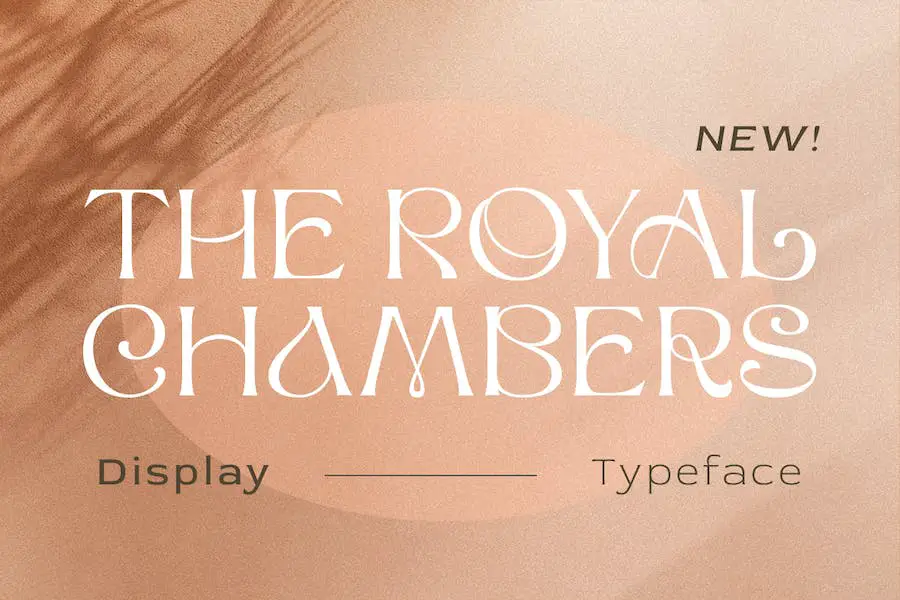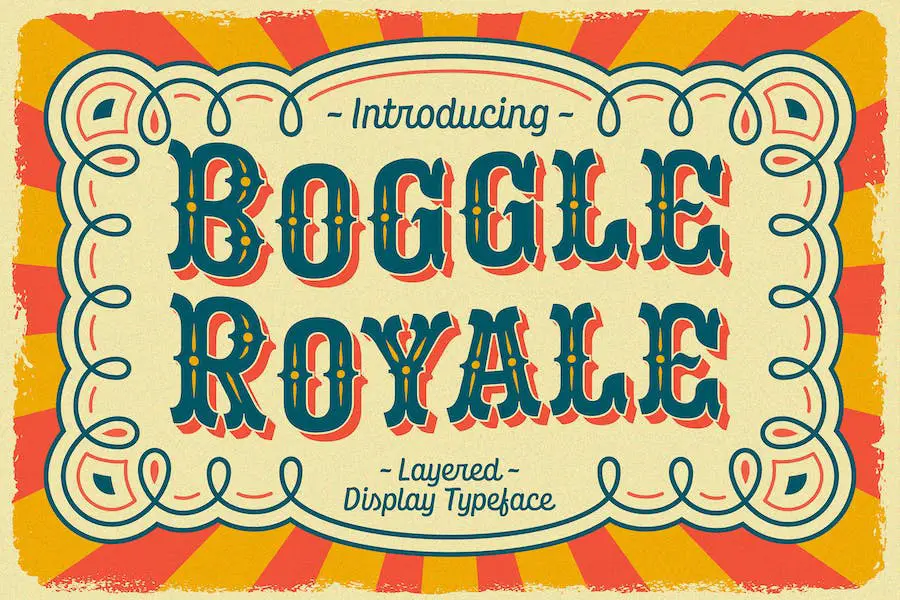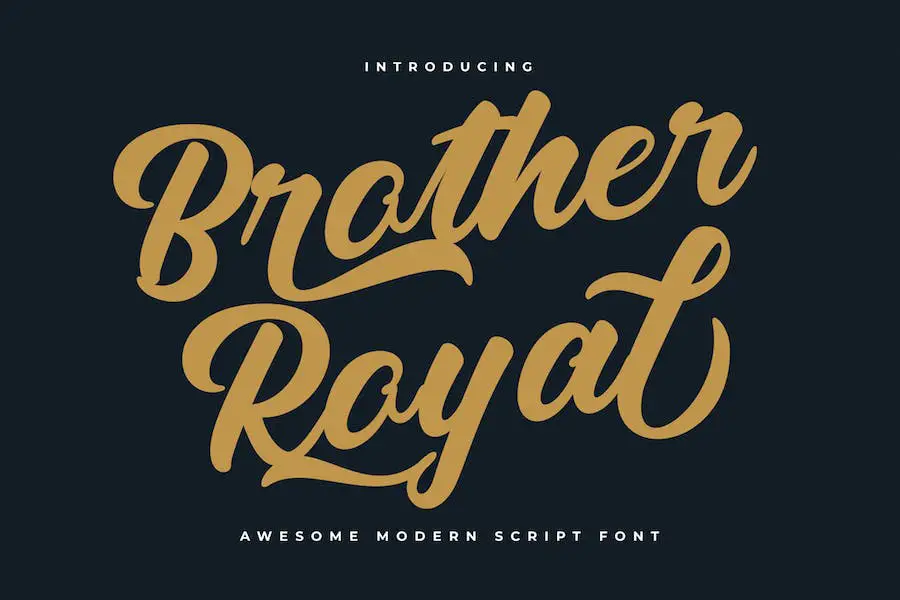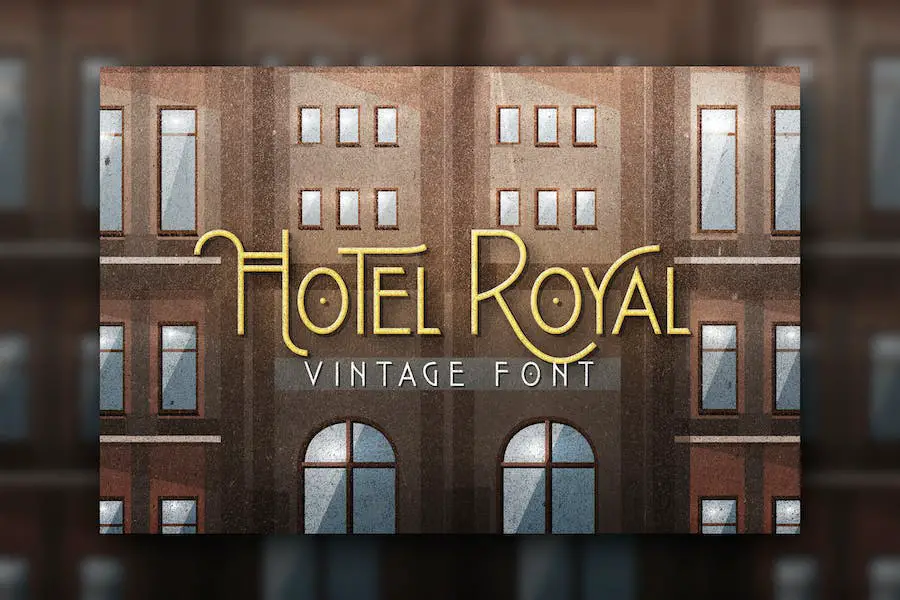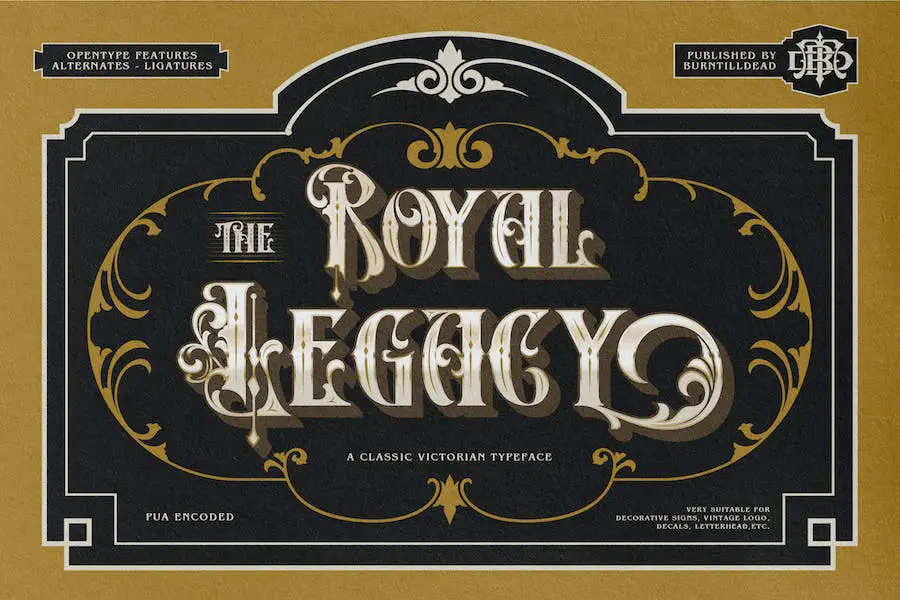
2023'ün En İyi 20 Kraliyet Yazı Tipi (Ücretsiz ve Premium)
Yayınlanan: 2023-09-10Projelerinizi bir sonraki seviyeye taşımak için mükemmel yazı tipini arayan bir grafik tasarımcı mısınız? Başka yerde arama! Bu blog yazısında sizi hem ücretsiz hem de premium seçeneklerle 2023'ün en iyi 20 royal yazı tipiyle tanıştıracağız. Ama merak ediyor olabilirsiniz, neden kraliyet yazı tiplerine ihtiyacım var?
Peki, konuya dalalım. Kraliyet yazı tipleri, projenizin tasarımını yükseltmenin ve ona zarafet ve gelişmişlik dokunuşu katmanın harika bir yoludur.
İster bir logo, web sitesi veya baskı tasarımı üzerinde çalışıyor olun, doğru yazı tipi seçimi büyük fark yaratabilir. Bu yazı tipleri kraliyet ailelerinin muhteşem estetiğinden ilham almıştır ve lüks ve gösterişli bir görünüm yaratmak için mükemmeldir.
Şimdi ayrıntılara geçelim. Bu yazımızda tasarımlarınızda kullanabileceğiniz 20 muhteşem royal yazı tipini sizlere sunacağız. İhtiyaçlarınıza ve bütçenize uygun mükemmel yazı tipini bulabilmeniz için size hem ücretsiz hem de premium seçenekler sunacağız.
Her yazı tipine kısa bir açıklama ve nasıl etkili bir şekilde kullanılabileceğine dair örnekler eşlik edecektir.
Öyleyse bir fincan kahve alın ve tasarımlarınızı sanat eserlerine dönüştürecek bu muhteşem kraliyet yazı tiplerinden ilham almaya hazırlanın. Gelin krallara ve kraliçelere uygun tipografi dünyasına dalalım ve keşfedelim!
En İyi Premium Royal Fontlar
Zarafet ve ince zevkin mükemmel bir uyum içinde buluştuğu Royal Fonts dünyasına hoş geldiniz. Bu bölümde tasarım projelerinize asil bir dokunuş katacak en iyi premium kraliyet yazı tiplerini sergiliyoruz.
Hedef kitlenizi büyüleyecek ve tasarımlarınızı yeni boyutlara taşıyacak bu muhteşem yazı tiplerini keşfedin ve keşfedin. Bu çarpıcı yazı tiplerini keşfetmek ve görsel hikaye anlatımının gerçek gücünün kilidini açmak için bir dakikanızı ayırın.
Kraliyet Dokunuşu
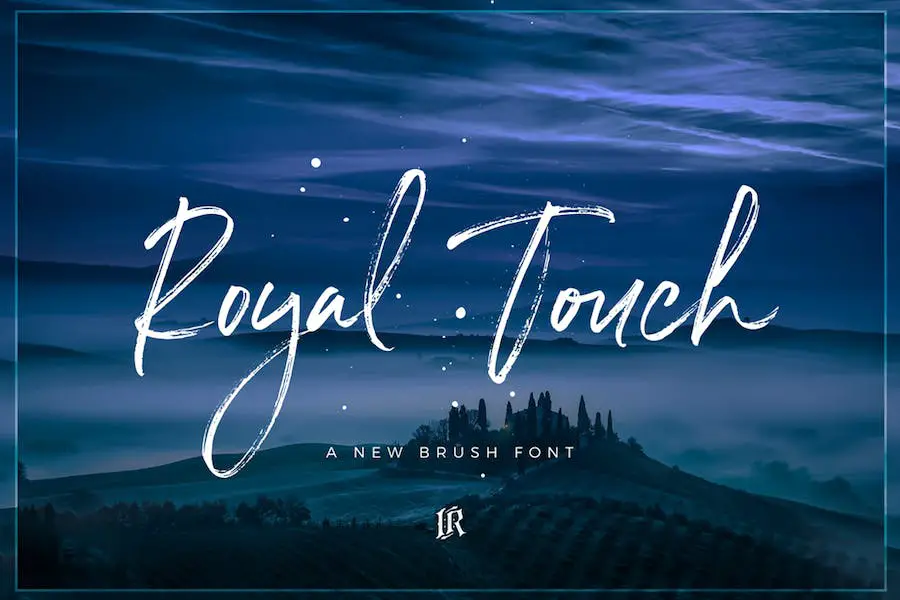
Royal Touch, her türlü tasarım projesine zarafet katacak, elle fırçalanmış çarpıcı bir yazı tipidir.
İster kraliyet temalı bir logo tasarlıyor olun, ister web siteniz için içerik oluşturuyor olun, ister bir dövme tasarımı üzerinde çalışıyor olun, Royal Touch mükemmel bir seçimdir. Zarif ve sofistike tarzı, projenizin kalabalığın arasından sıyrılmasına ve kalıcı bir izlenim bırakmasına yardımcı olacaktır.
Bu yazı tipini diğerlerinden ayıran şey çok yönlülüğü ve kullanım kolaylığıdır. Adobe Illustrator ve Google Fonts gibi çeşitli tasarım yazılımlarına kolayca entegre edilebildiği için her seviyeden tasarımcının erişimine açıktır.
Le Royale
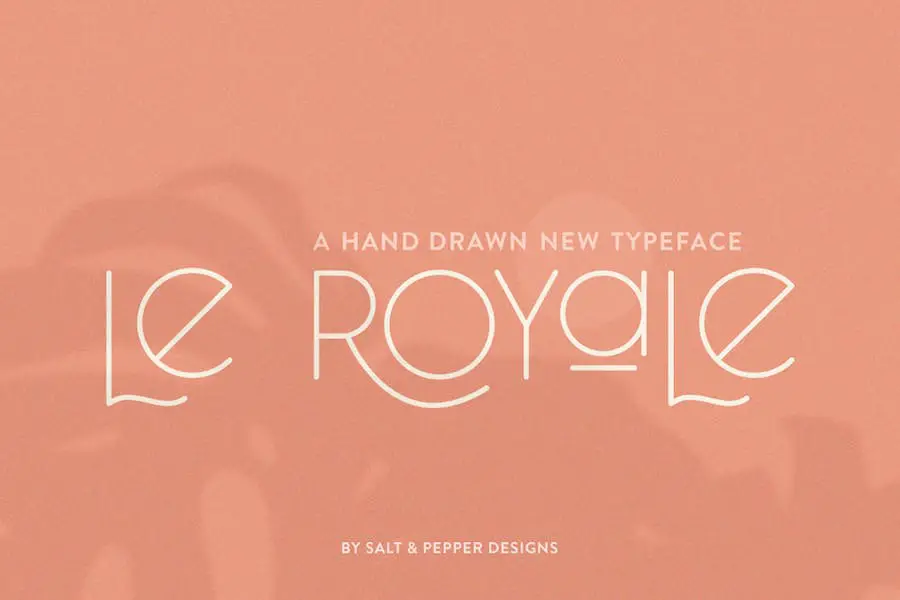
Le Royale, Salt & Pepper Designs tarafından oluşturulan inanılmaz derecede zarif yeni bir yazı tipidir. Klasik sans yazı tiplerine benzersiz bir dokunuşla saygı duruşu niteliğinde olup tasarımlarınıza benzersiz bir dokunuş katmanıza olanak tanır.
İster profesyonel bir grafik tasarımcı olun, ister yalnızca projelerinin tasarımını geliştirmek isteyen biri olun, bu yazı tipinin çalışmanızı geliştireceği kesindir.
Zarif ve şık görünümüyle Le Royale, her projeye sofistike bir dokunuş katıyor. Klasik ama aynı zamanda ayırt edici tasarımı, onu diğer yazı tiplerinden ayırarak göz alıcı başlıklar, logolar ve marka kimlikleri oluşturmak için mükemmel kılar.
Kraliyet Harikası
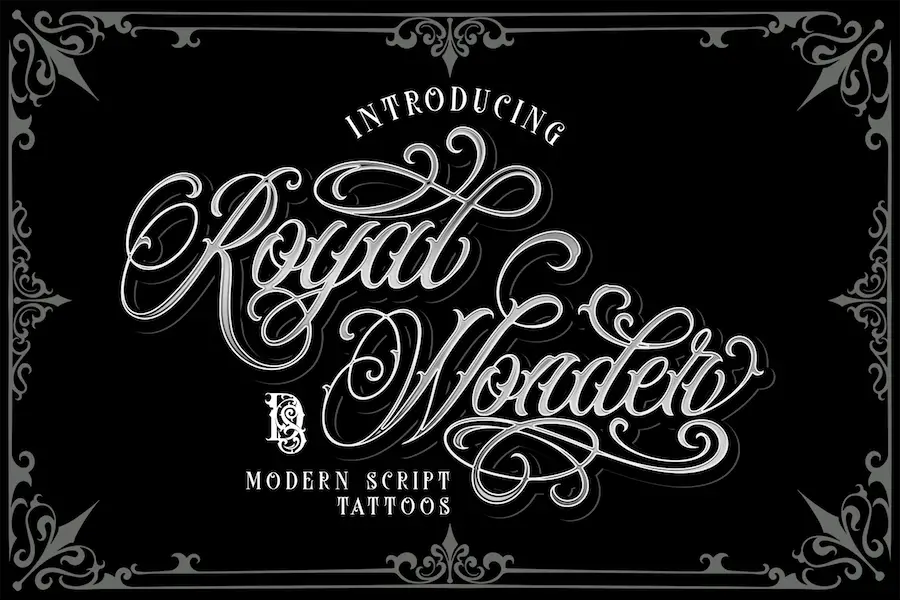
Royal Wonder, her projeye zarafet ve benzersizlik katan çarpıcı bir siyah harf yazı tipidir. Farklı görünümüyle göz alıcı logolar, poster başlıkları, manşetler, ambalaj tasarımları, rozetler, giyim markası logoları ve vintage esintili tasarımlar oluşturmak için mükemmeldir.
Bu yazı tipinin çok yönlülüğü, projelerini geliştirmek isteyen her grafik tasarımcı için onu mükemmel bir seçim haline getiriyor. Güzelliği, dikkat çekme ve kraliyet ve incelik duygusunu aktarma yeteneğinde yatmaktadır.
Royal Wonder yazı tipi özellikle ürün logoları oluşturmak için çok uygundur. Karmaşık ve süslü tasarımı, marka kimliğini anında yükselterek ona ihtişam ve zarafet duygusu verir.
Kraliyet Tereyağı
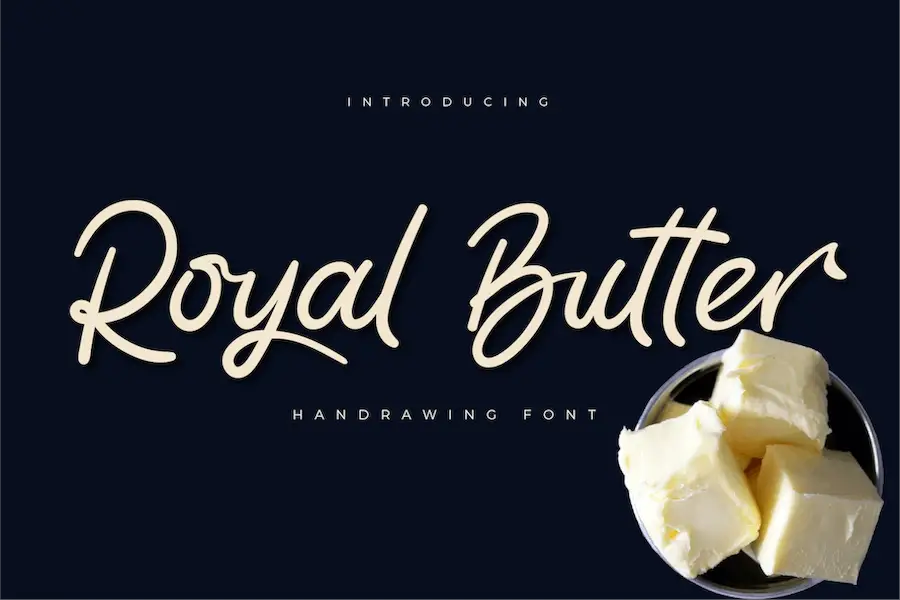
Royal Butter, çekicilik ve zarafet yayan bir yazı tipidir. Düğün davetiyeleri, teşekkür kartları, alıntılar, tebrik kartları, logolar ve kartvizitler gibi çeşitli tasarım projelerine çarpıcı bir dokunuş katar.
Royal Butter, el yazısı tarzıyla her tasarıma kişisel ve benzersiz bir his katıyor. PUA kodludur ve tüm farklı gliflere ve desenlere erişmeyi kolaylaştırır.
Yazı tipi, tasarımlarınızın genel estetiğini artıran değişken bir taban çizgisine, düzgün çizgilere, güzel gliflere ve çarpıcı alternatiflere sahiptir.
İŞARET YOK
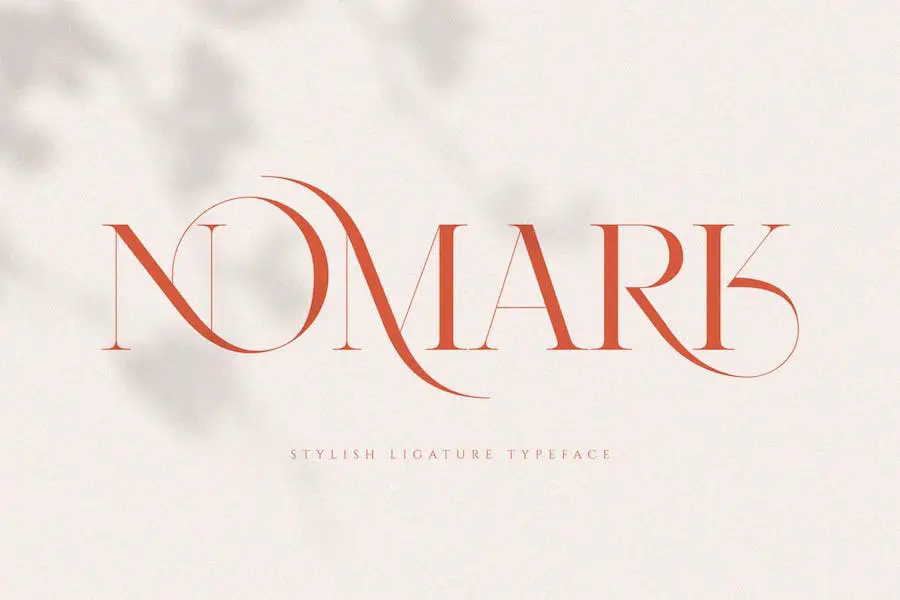
NOMARK yazı tipi, modernliği bir miktar nostaljiyle birleştiren sofistike ve şık bir serif yazı tipidir. Projelerini geliştirmek için zarif ve şık bir yazı tipi arayan grafik tasarımcıları için mükemmeldir.
NOMARK, kullanıma hazır ligatür ve serif özellikleriyle logo ve çeşitli tasarım amaçları için ideal bir seçimdir. Tasarımlarınıza zarafet, stil, sınıf, şıklık ve modernlik dokunuşu katmak istiyorsanız bu yazı tipi özellikle sizi düşünerek tasarlanmıştır.